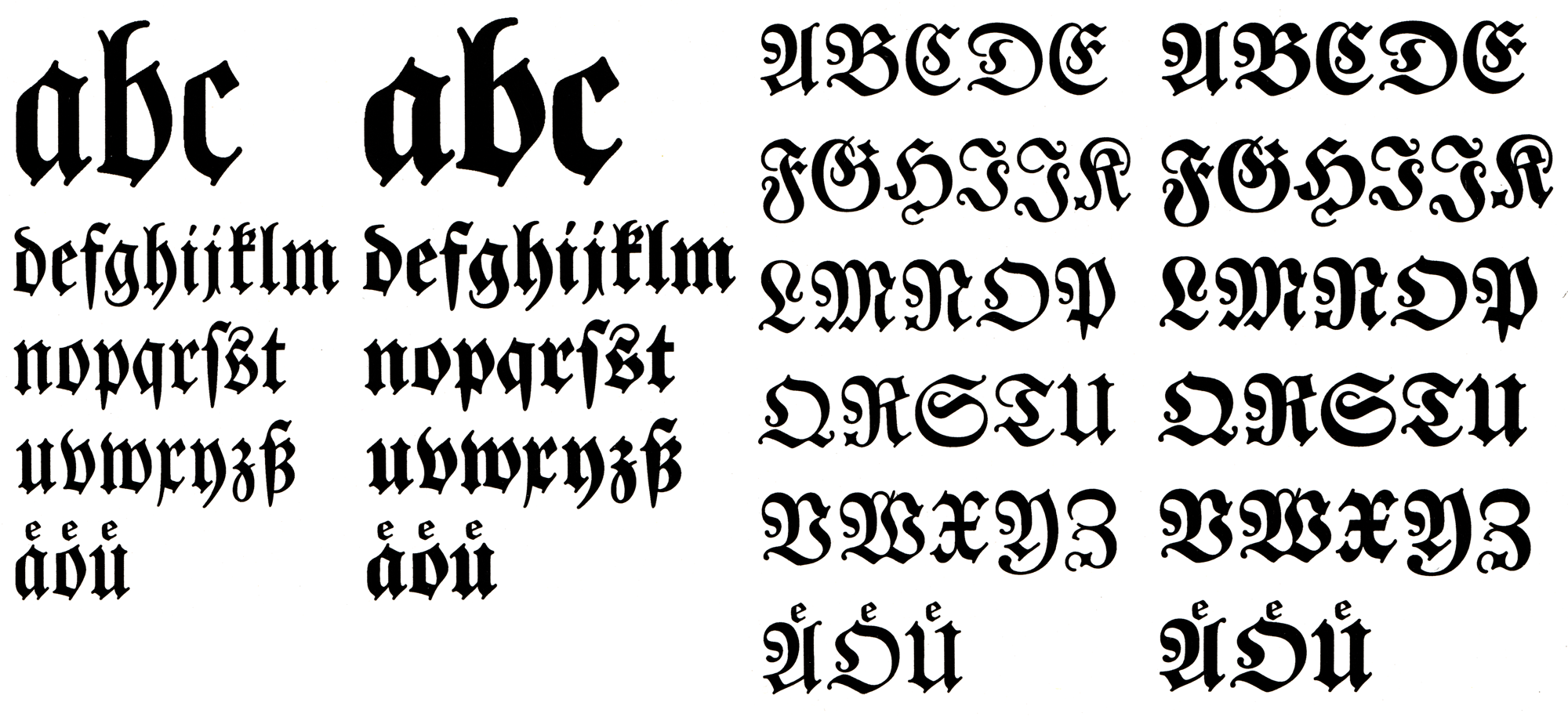
- circa 1985
- Gebrochene Schrift
Die Bezeichnung Luthersche Fraktur bezieht sich auf die ursprüngliche Entstehung bei der Egenolff-Lutherschen Schriftgießerei in Frankfurt am Main um 1700. Die Schrift blieb bis ins 20. Jahrhundert hinein erfolgreich, dann vor allem über die Veröffentlichung über die D. Stempel AG in Frankfurt am Main.
Bei Typoart wurde die Schrift in den 1980er-Jahren durch Volker Küster neu bearbeitet. Die noch dekorativeren Großkegelversionen wurden von Herbert Lemme entworfen. (Küster verließ zu dieser Zeit die DDR und arbeitete dann für die Scangraphic Dr. Böger GmbH in Wedel bei Hamburg, wo die Schrift ebenfalls veröffentlicht wurde.)
Elsner+Flake hat die Schriften auf Basis der Originaldaten von Typoart digital in drei optischen Größen (TB/TI/TH) angeboten.